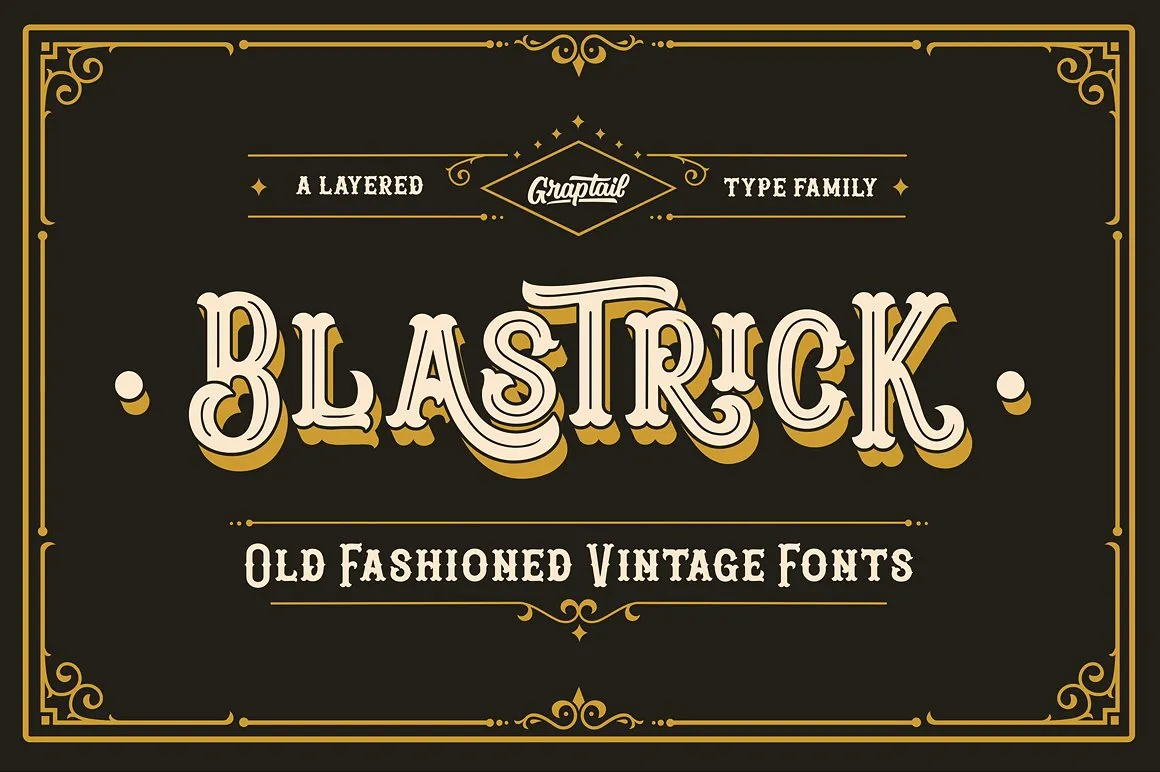
Blastrick Vintage Font – Download Grátis
Introduzimos Blastrick! Esta fonte premium foi criada pelo designer Graptail, disponível no Creativemarket. Agora, é uma oportunidade única para você ter Blastrick gratuitamente para download. Blastrick é um sistema de tipo vintage completo com infinitas possibilidades de design usando combinações diferentes de fonts e cores. Este tipo é projetado para criar efeitos 3D reais adicionando a fonte do sombra, ou mesmo apenas usando as letras maiúsculas dos cortes padrão e bold para arte stark. Blastrick não só transforma o modo como você cria grafismo, mas também oferece uma infinidade de possibilidades criativas sem estarem limitados por um layout específico. É perfeito para aqueles que desejam incorporar um toque vintage ao seu design ou estão buscando criar algo realmente único e impressionante.